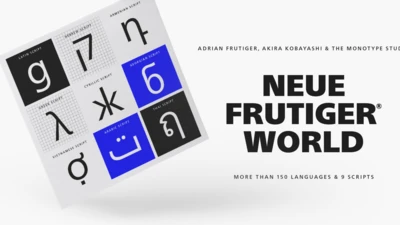
Isuzu AN
Monotypeは、世界トップクラスの商用車メーカー、いすゞ自動車株式会社の専用書体を制作しました。欧文書体については、社内で使用していたAvenir Nextの硬質な印象を残しながら、画面上での可読性や実用性を考慮して調整。8ウェイトの専用書体Isuzu ANを制作しました。Avenir Next の多言語ファミリーを使用したよりグローバルな展開も可能です。また和文書体には、Avenir NextにあわせてMonotypeが開発したShorai Sansを採用し、Isuzu ANと組み合わせて使える4ウェイトが指定されました。
いすゞ自動車の専用書体は、機能性とブランドを兼ね備えた書体として、同社の製品やメッセージに幅広く使われる予定です。
Isuzu AN
Monotypeは、世界トップクラスの商用車メーカー、いすゞ自動車株式会社の専用書体を制作しました。欧文書体については、社内で使用していたAvenir Nextの硬質な印象を残しながら、画面上での可読性や実用性を考慮して調整。8ウェイトの専用書体Isuzu ANを制作しました。Avenir Next の多言語ファミリーを使用したよりグローバルな展開も可能です。また和文書体には、Avenir NextにあわせてMonotypeが開発したShorai Sansを採用し、Isuzu ANと組み合わせて使える4ウェイトが指定されました。
いすゞ自動車の専用書体は、機能性とブランドを兼ね備えた書体として、同社の製品やメッセージに幅広く使われる予定です。
Southwest Sansは、サウスウエスト航空のブランドリニューアルのために新しいロゴを作るところからスタートしたプロジェクトです。
これにより、空港の搭乗案内やウェブサイト、ピーナッツの袋、クーポンからナプキンまで、サウスウエスト航空の「声」が一つになりました。
Southwest Sans
Southwest Sansは、サウスウエスト航空のブランドリニューアルのために新しいロゴを作るところからスタートしたプロジェクトです。
これにより、空港の搭乗案内やウェブサイト、ピーナッツの袋、クーポンからナプキンまで、サウスウエスト航空の「声」が一つになりました。
「MEVIUS」は世界的な市場を前提に、モノタイプ社タイプディレクター小林章がロゴデザインを担当しました。
長く使うことを考えて、あえてアイキャッチを排除し、落ち着いた印象のデザインを採用しまた。これまで日本の大手企業が取らなかった海外にも新ブランド浸透を図るブランディング戦略と言えます。
Mevius
「MEVIUS」は世界的な市場を前提に、モノタイプ社タイプディレクター小林章がロゴデザインを担当しました。
長く使うことを考えて、あえてアイキャッチを排除し、落ち着いた印象のデザインを採用しまた。これまで日本の大手企業が取らなかった海外にも新ブランド浸透を図るブランディング戦略と言えます。
SST
SST®フォントは、広告やwebサイトだけでなく、店頭でのプロモーション、商品、サービス、取扱説明書に至るまで、ソニー全体で使うためのコーポレートフォントです。初期段階から英語や日本語はもちろん、ギリシャ語やタイ語、アラビア語にも対応するなど、これまでにないスケールで進められました。
SST®
SST®フォントは、広告やwebサイトだけでなく、店頭でのプロモーション、商品、サービス、取扱説明書に至るまで、ソニー全体で使うためのコーポレートフォントです。初期段階から英語や日本語はもちろん、ギリシャ語やタイ語、アラビア語にも対応するなど、これまでにないスケールで進められました。
Dominos
自由な組み合わせを可能にするモジュール式 マルチレイヤーフォントPizza Press書体
ドミノ・ピザを担当していたアメリカの広告代理店Crispin Porter + Bogusky社の依頼により、モノタイプの書体デザイナーのテランス・ワインジールが制作した書体のご紹介です。
Pizza Press
自由な組み合わせを可能にするモジュール式 マルチレイヤーフォントPizza Press書体
ドミノ・ピザを担当していたアメリカの広告代理店Crispin Porter + Bogusky社の依頼により、モノタイプの書体デザイナーのテランス・ワインジールが制作した書体のご紹介です。
Neue Frutiger World
150以上の言語をサポートした、人になじむ書体ファミリー Neue Frutiger World
多言語での使用を想定して開発され、150以上もの言語・文字体系に対応しています。ウェイトは10ウェイトと、それぞれにイタリックも用意されています。温かみがありながらも、機能性・可読性に優れ、世界中で一貫したブランドイメージ、そして「声」を伝えることができます。
Neue Frutiger World
150以上の言語をサポートした、人になじむ書体ファミリー Neue Frutiger World
多言語での使用を想定して開発され、150以上もの言語・文字体系に対応しています。ウェイトは10ウェイトと、それぞれにイタリックも用意されています。温かみがありながらも、機能性・可読性に優れ、世界中で一貫したブランドイメージ、そして「声」を伝えることができます。